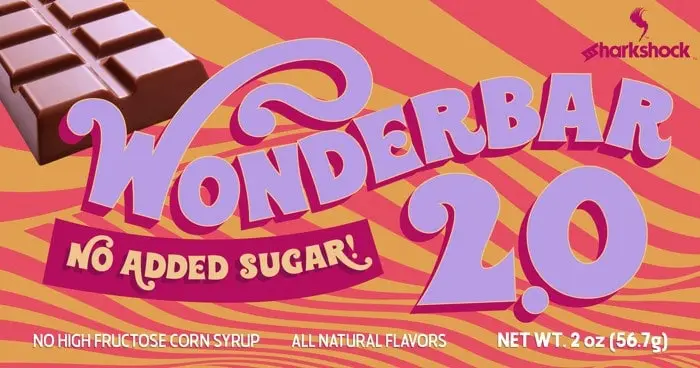
A fonte Wonderbar 2.0 Display é uma nova versão atualizada do popular tipo retro, oferecendo uma aparência única e vibrante para uso em diversos ambientes. Embora possa parecer semelhante à sua versão anterior ao primeiro olhar, muitos caracteres foram completamente redesenhados, resultando num aspecto mais fluido e sofisticado dos contornos ondulantes e curvas. Este tipo deixa um ar mais ordenado, com linhas mais retas e menos abstrações na simulação da natureza do texto. Outras alterações incluem uma métrica mais apertada e a adição de caracteres círlicos, oferecendo ainda mais flexibilidade ao designer. Ideal para aplicar em livros infantis, cartazes ou convites de aniversário, Wonderbar 2.0 Display cria um impacto visual divertido e vibrante que se encaixa perfeitamente com temas retro e crianças. Com o design de uma fonte tão charmosa e versátil, é fácil ver por que esta é uma escolha popular para designers buscando dar vida a seus projetos digitais.